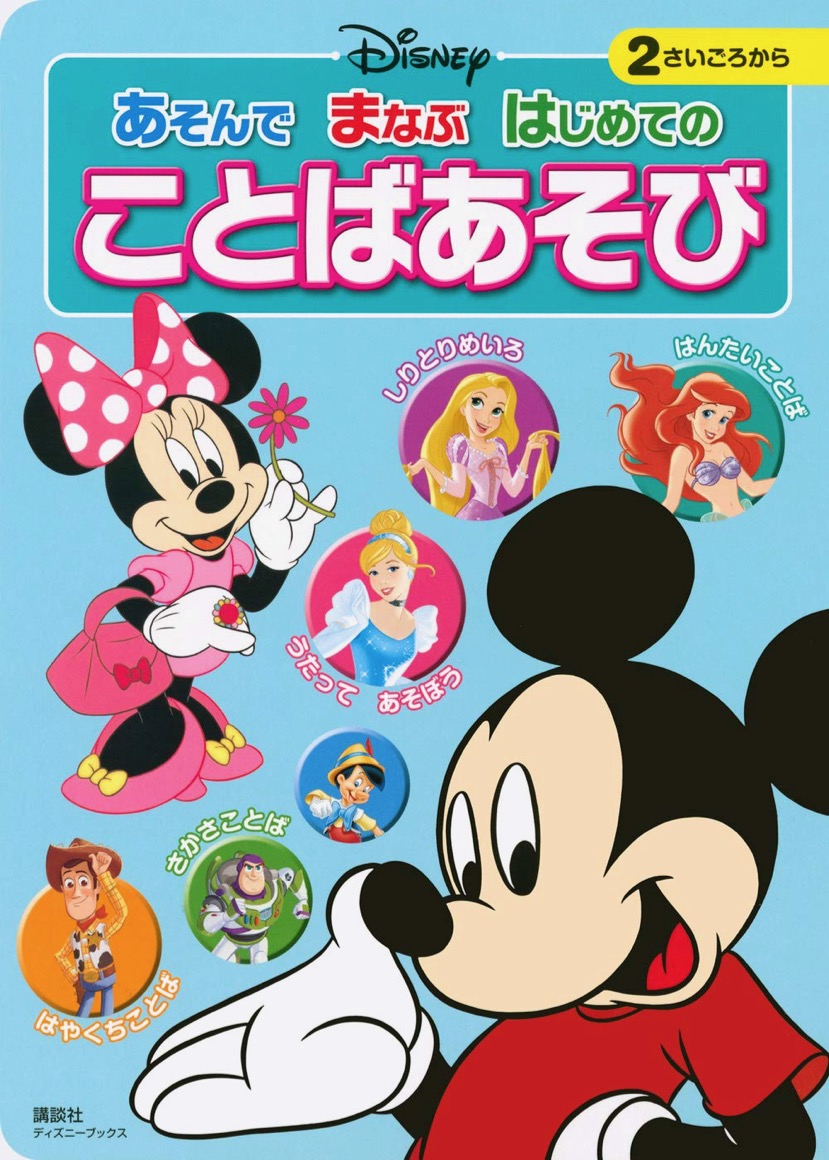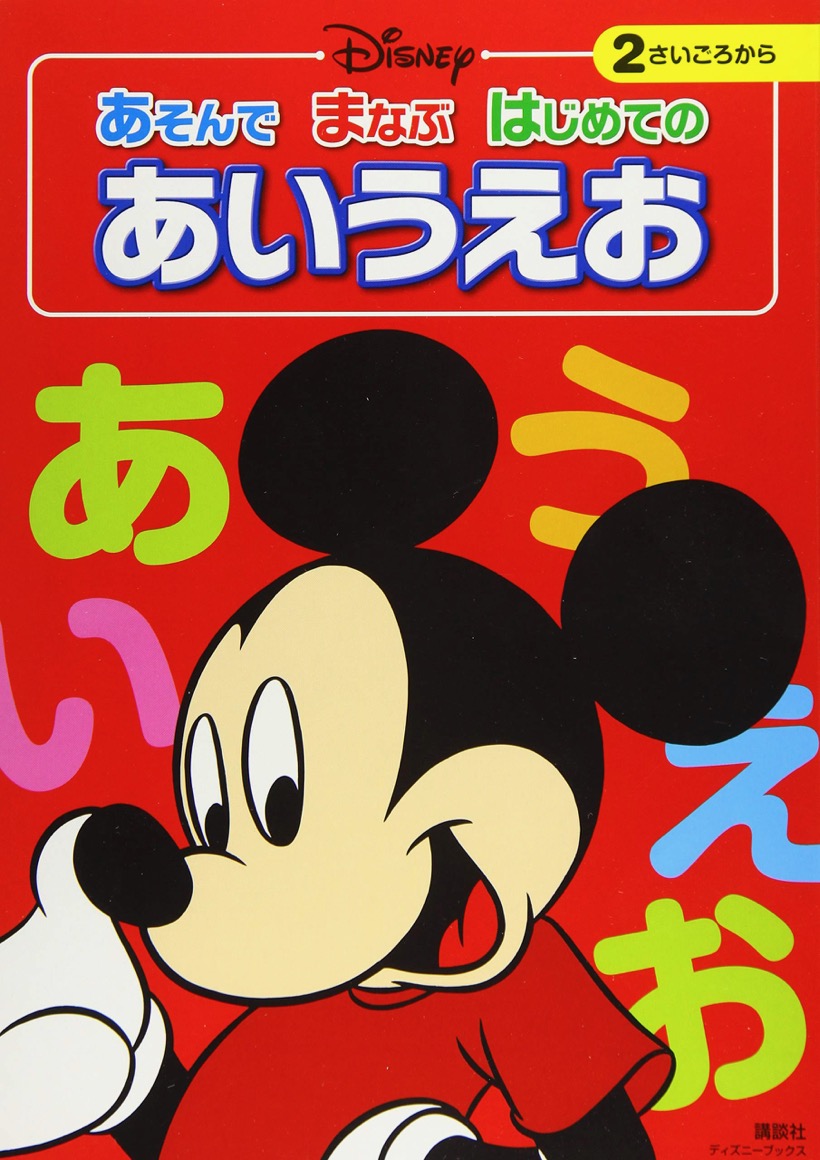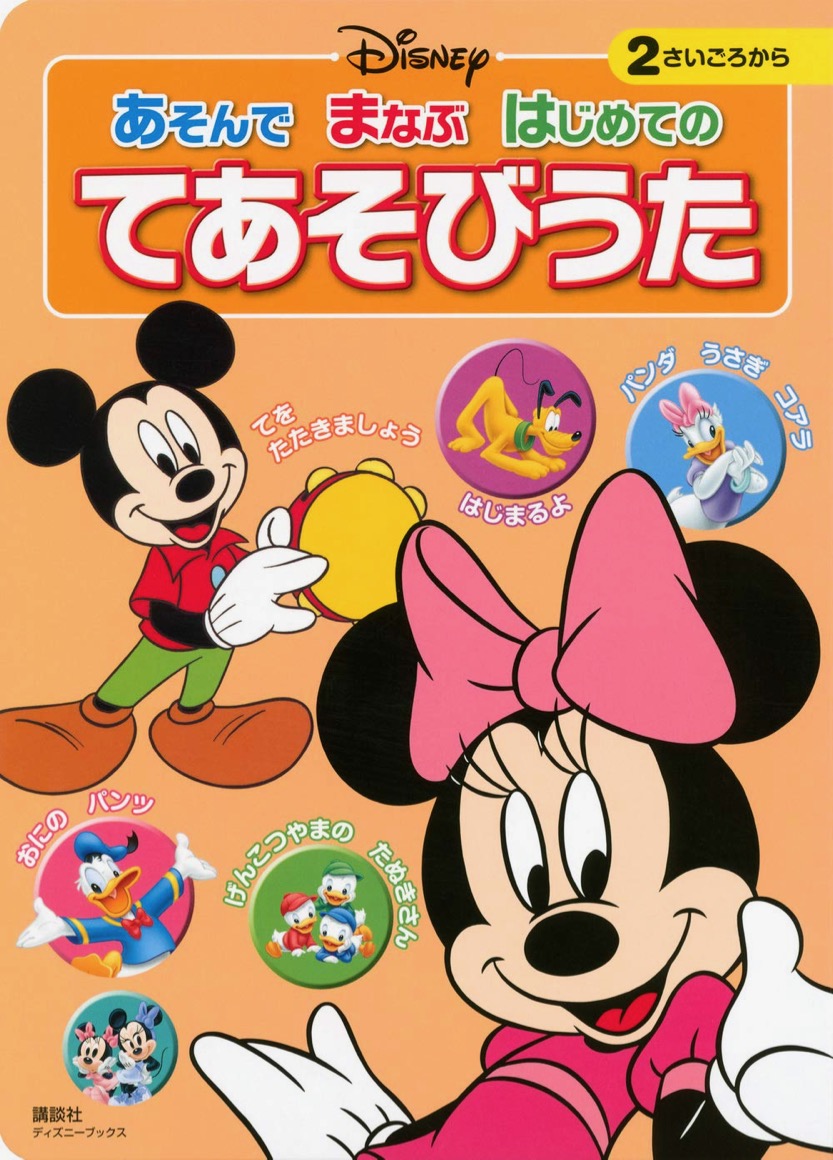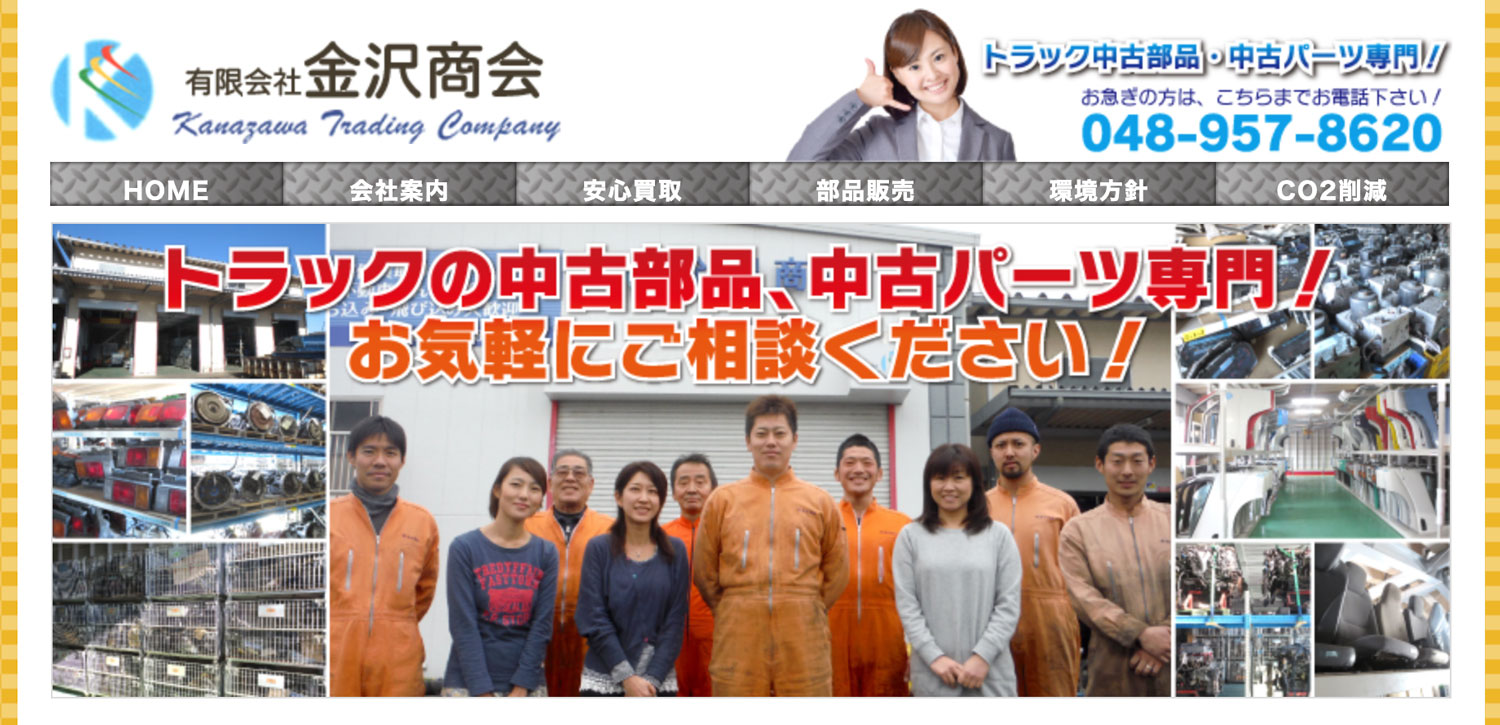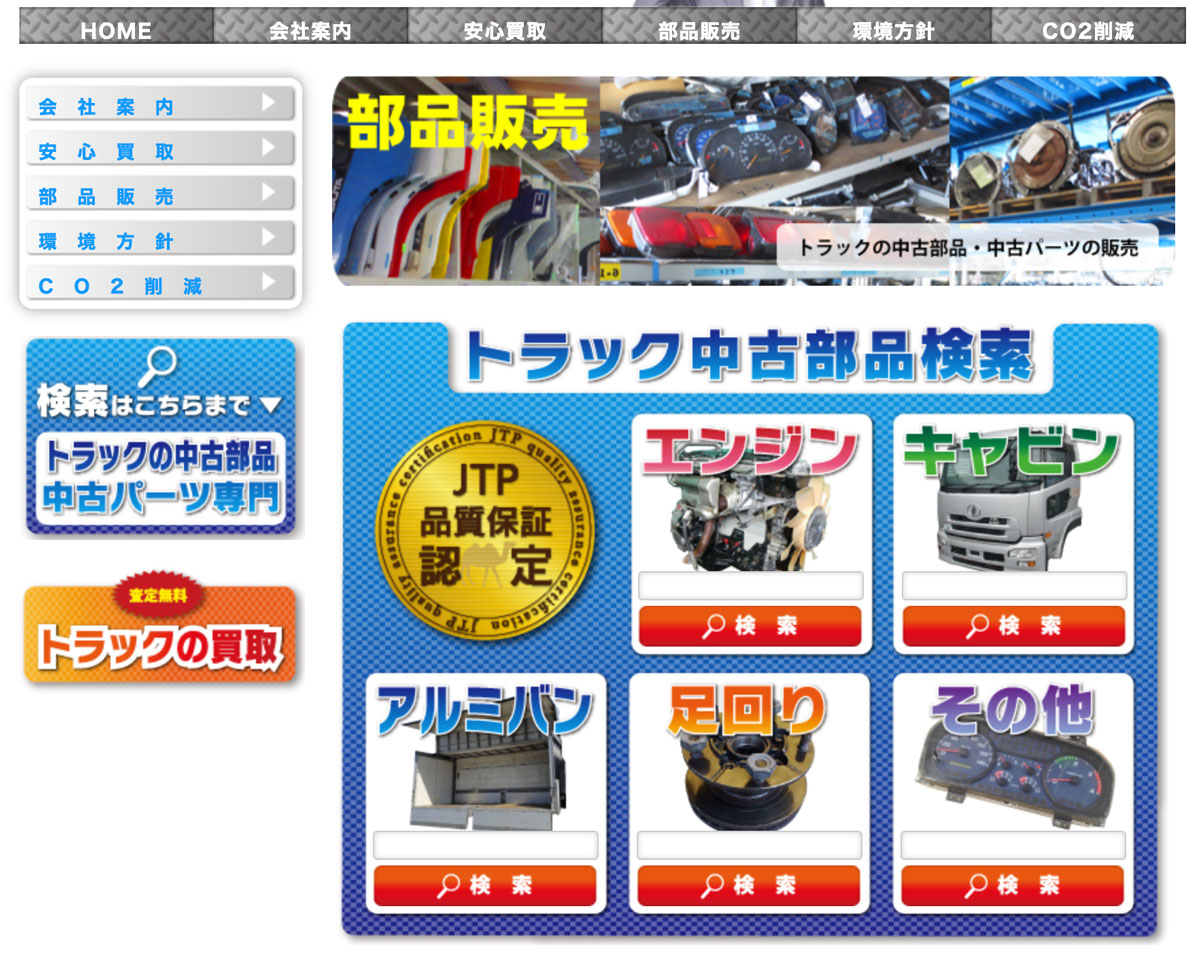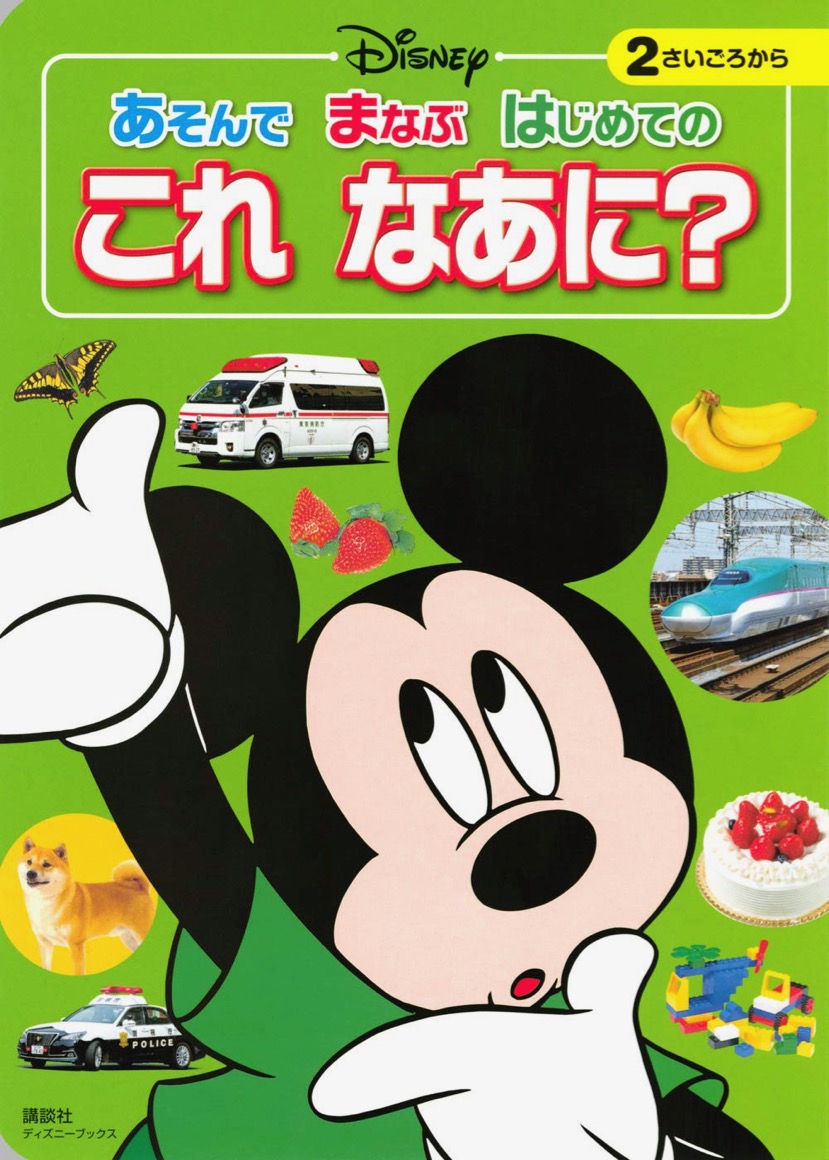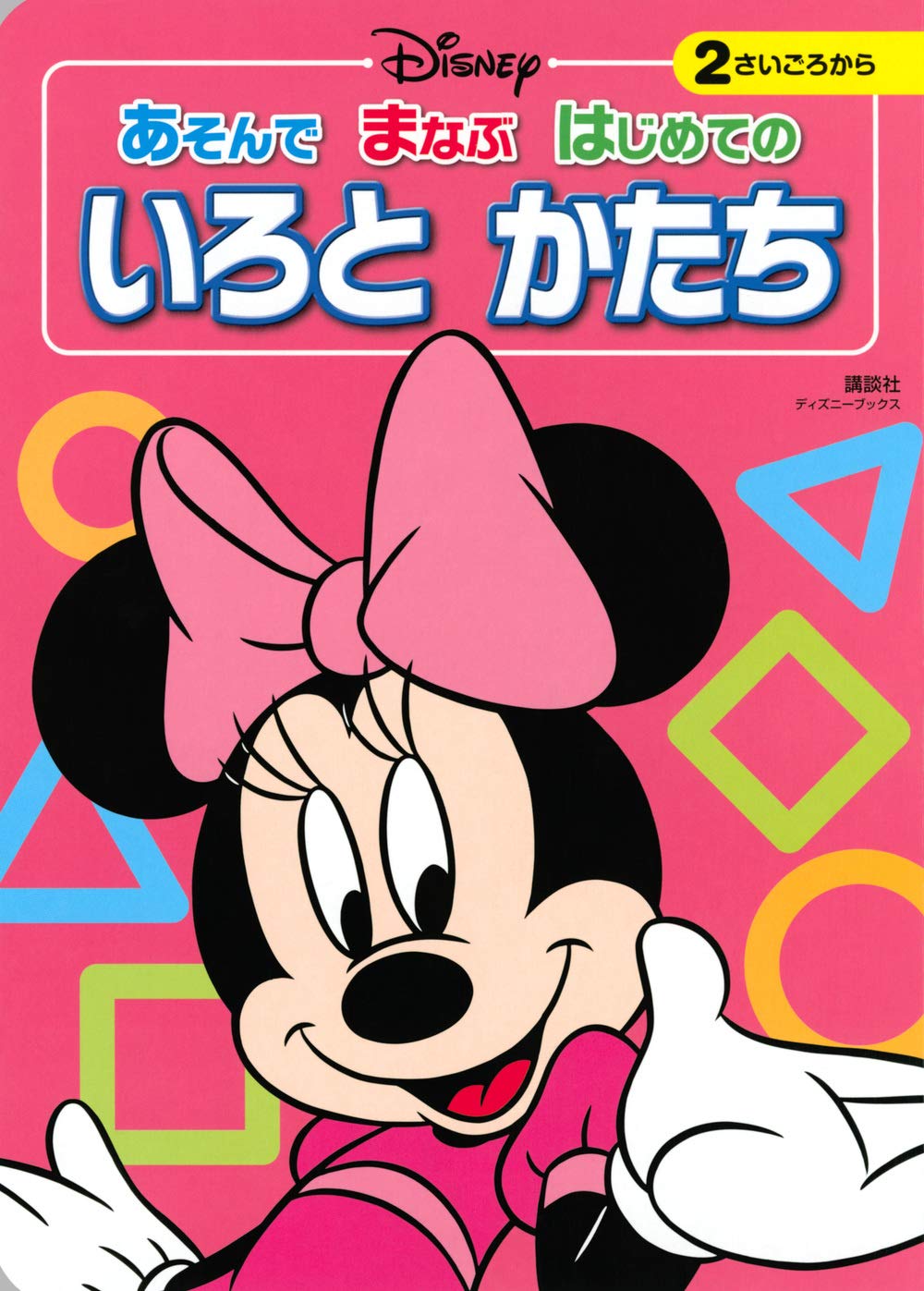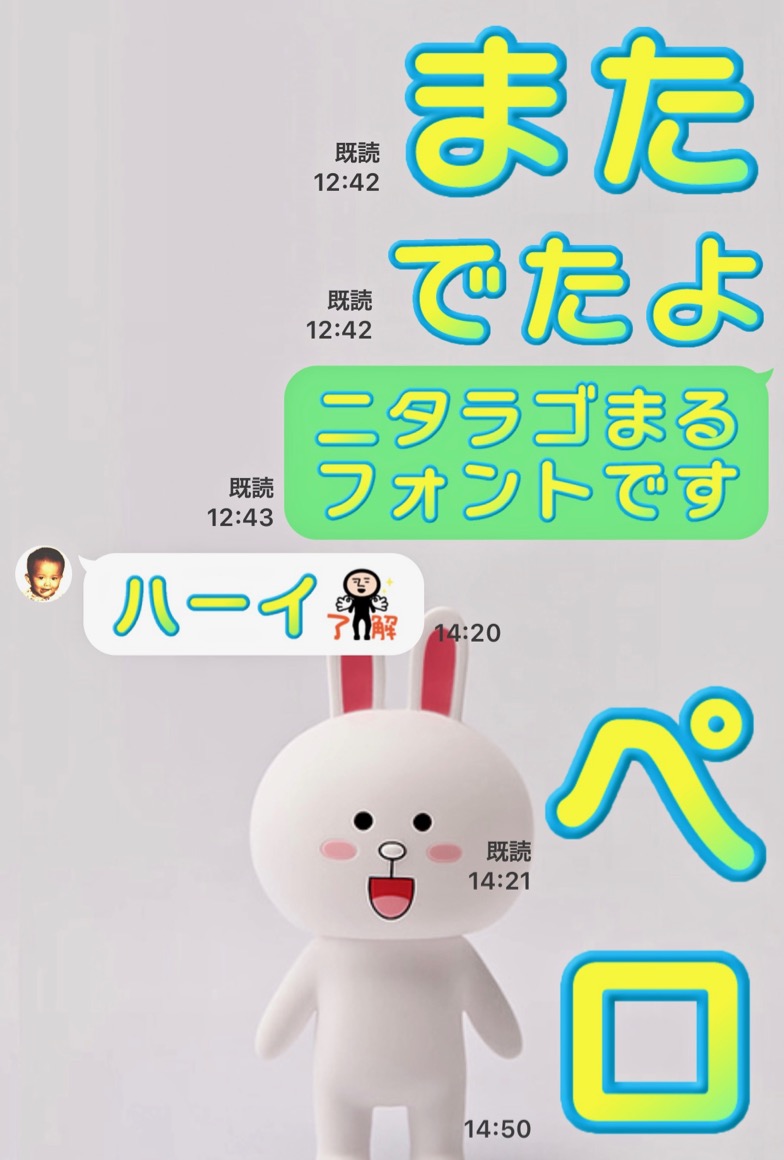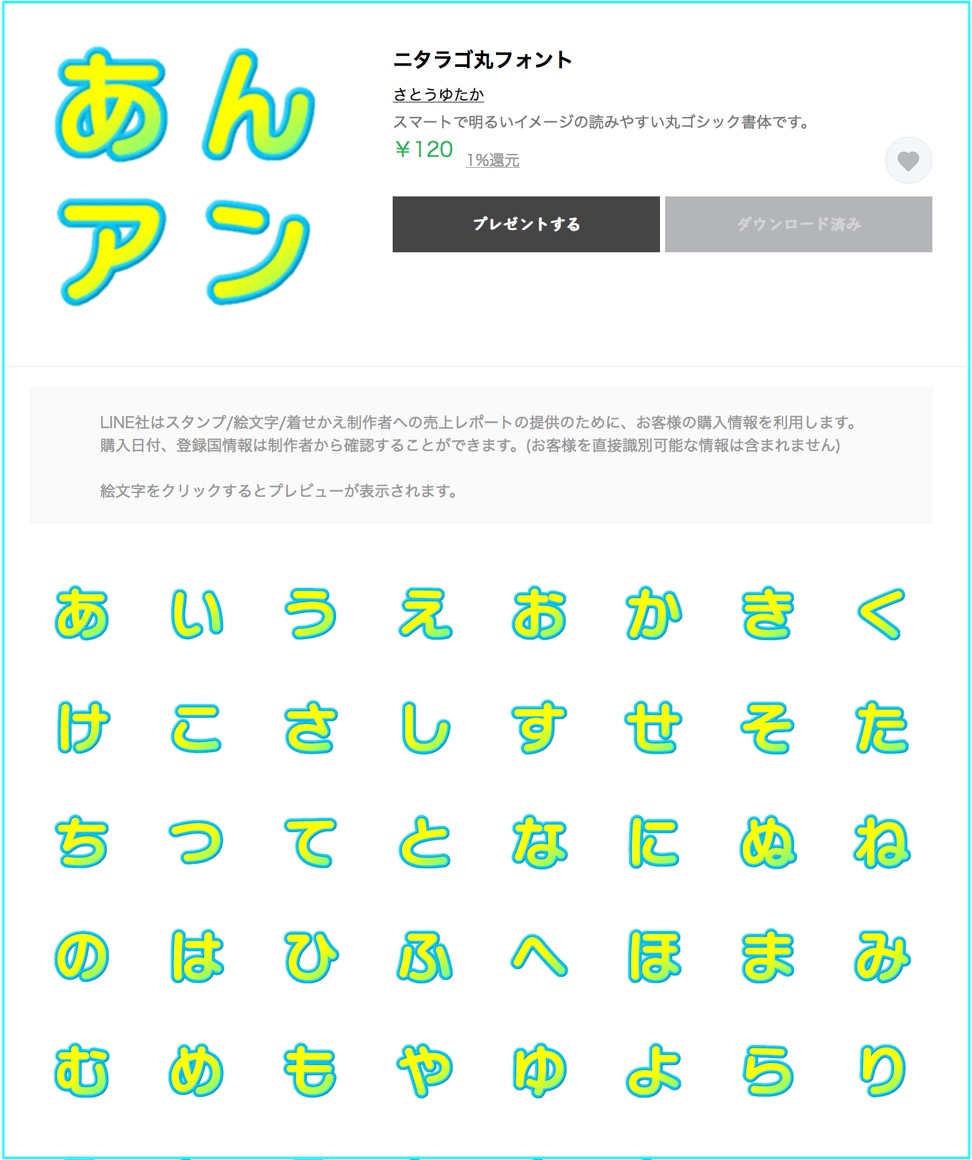
企業向けツール さとうゆたか
あちこちで広告を見かけますね。
これも…。
もうひとつ…。
映画タイトル さとうゆたか
韓国ドラマかな。
これはポスター?
これも…。
濁点とか「ン」の1画目とか、手を入れられてるけど…。
うまトマ さとうゆたか
季節限定商品かな。
あ さとうゆたか
こちらは看板…。
柔らかい曲線が醸し出す、ゆったりした明るい雰囲気が、飲食業界に好まれているようだ。
マクドナルド さとうゆたか
夏にぴったりなウマ辛味の新作!「スパイシーベーコンポテトパイ」が8/2(水)から期間限定で登場!
これも…。
MBSの番組 takumi
MBSの番組「よしもと新喜劇NEXT〜小籔千豊には怒られたくない」でニタラゴフォントが使われていました。
大きいサイズで、字間も気持ち良くツメられていると思います。
短いフレーズで、このくらい大きく使われると気持ちイイですね…。
イベント広告画像 さとうゆたか
今日と明日の開催。
これも…。
期間限定 さとうゆたか
マクドナルドの期間限定商品の広告画像。
テロップにニタラゴルイカ あいまい
ニタラゴルイカのようですね。
本の表紙 さとうゆたか
書名:秘密の大作戦!フードバンクどろぼうをつかまえろ!
著者:オンジャリQ、ラウフ、千葉 茂樹
発行:あすなろ書房
映画の題名ロゴ さとうゆたか
濁点の大きさや読点の形から、ニタラゴルイカが使われていると思う。
実際のタイトル。
予告編を見たけど、面白そうだ…。